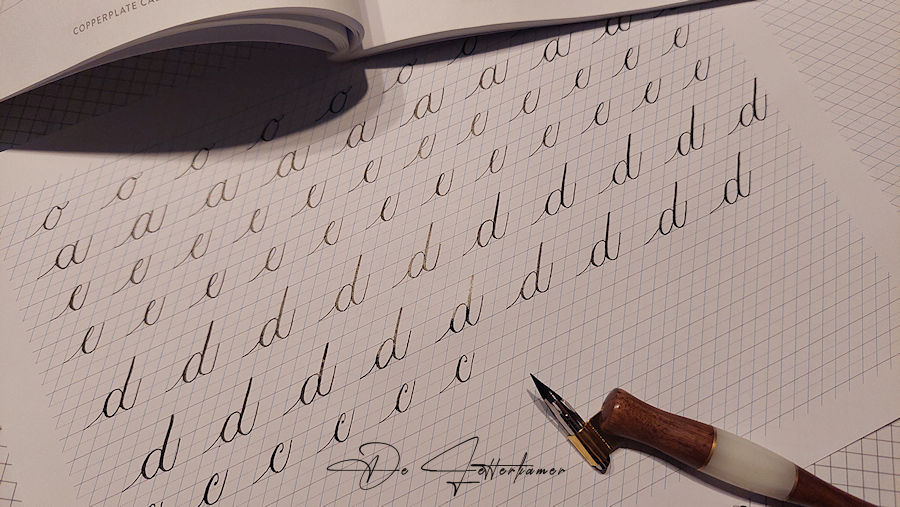
Er is toch weer vlug een week voorbij gegaan, ik dacht bij mezelf, neem pen en inkt bij de hand en begin er aan. Eventjes weg van alles rondom mij. Ondertussen zit ik aan groep 2: ovals, we gaan nu e, d en c oefenen. Eerst heb ik enkel basisvormen gedaan om mijn handeling terug in mijn vingers te krijgen. Ik merk dat het dan veel beter gaat.
Ziehier een voorbeeld tot waar mijn kunnen zit. Eigenlijk gaat het veel beter dan ik verwacht had.
Mja, bij mijn gewoon dagelijks schrift is het eerder slordig, ik schrijf groot en rond, en niet altijd gelijk. Dus ik had dit niet verwacht, als ik me er aan toe leg, en ik let op hoe ik mijn pen met de druk mee volg, dan lukt het vrijwel goed. Mijn dochter kijkt mee en is eigenlijk wel verrast, ze heeft dit ook al gedaan op school. Mijn “teacher” naast mij.
De volgende keer ga ik zowel groep 1 en 2 na elkaar oefenen. Dus het wordt vervolgd.